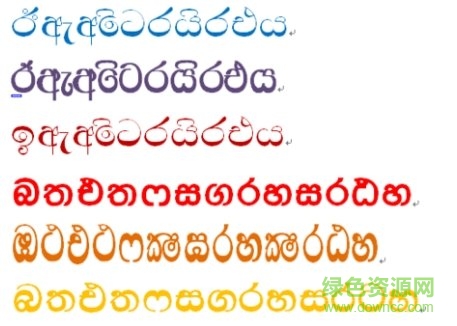
僧伽羅語字體ttf
僧伽羅語字體是一款小語種字體,專為Sinhala地區(qū)的朋友打造,方便用戶直接使用在Windows系統(tǒng)上,帶來更多的使用體驗(yàn),綠色資源網(wǎng)誠意推薦!
Sinhala僧伽羅語簡介
僧伽羅語(Sinhala/Sinhalese),屬印歐語系、印度語族,和印度北部諸語言相近,是斯里蘭卡主體民族僧伽羅族的語言,也是斯里蘭卡的主要官方語言。僧伽羅語形成于公元前六世紀(jì)。
僧伽羅語體ttf
僧伽羅語最早的文字是婆羅米字母,到7~8世紀(jì)才逐漸演變?yōu)樯ち_體,一直沿用至今,自左而右書寫。這種環(huán)形的僧伽羅體和印度南部達(dá)羅毗荼諸語言的字母近似。已發(fā)現(xiàn)的最早文字是公元前3世紀(jì)的石刻銘文。純僧伽羅字母共36個(gè),加上18個(gè)表示梵語語音的字母,共計(jì)54個(gè)。